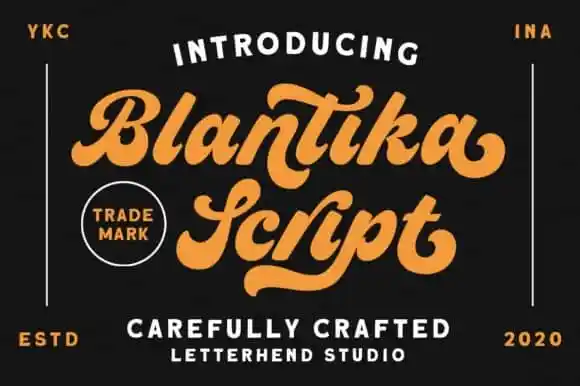
Blantika Script Font – Download Grátis
Blantika Script é uma tipografia de script vintage que foi criada pelo Letterhend Studio. Este tipo de fonte forte e vibrante adquire uma aparência confiante e dinâmica, perfeita para dar um toque nostálgico a qualquer projeto. Blantika Script inclui letras maiúsculas e minúsculas, números romanos, uma ampla gama de pontuação, alternativas de caracteres, set personalizados e ligaduras. Perfeito para adicionar um toque memorável ao seu design, Blantika Script é a escolha perfeita para quem busca uma fonte que carrega o encanto dos anos 50 e 60. Não importa se você está trabalhando em cartões de presentes, infográficos ou designs para revistas, Blantika Script proporcionará um toque único e memorável a qualquer projeto.